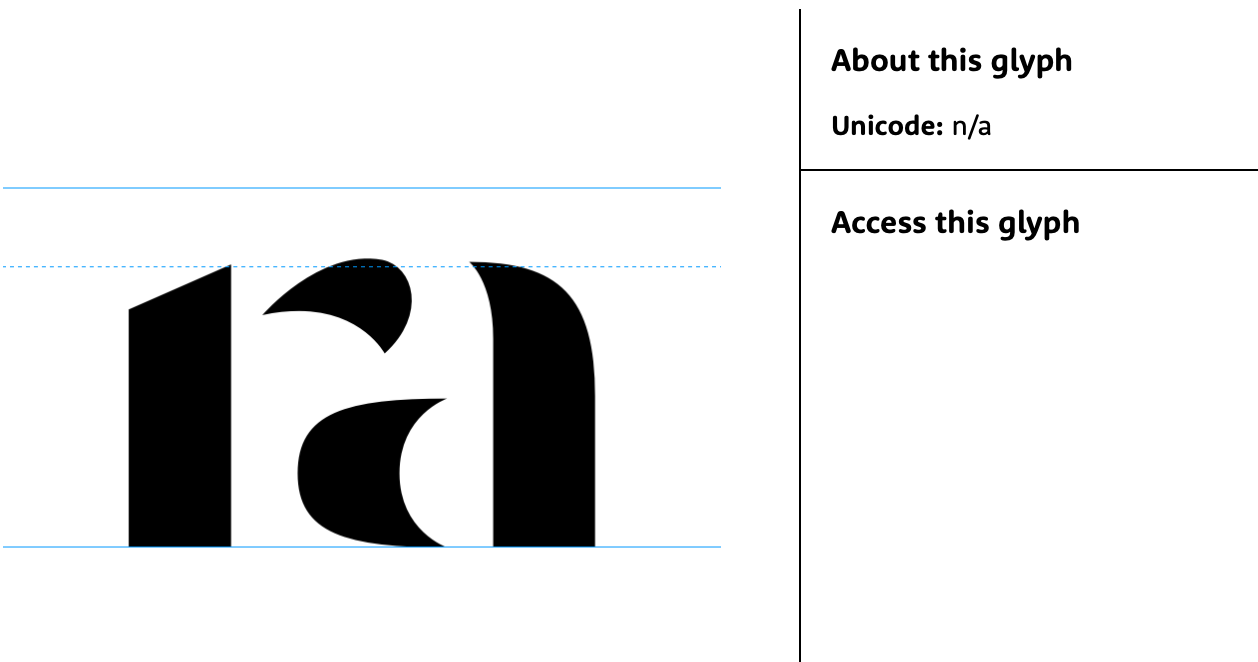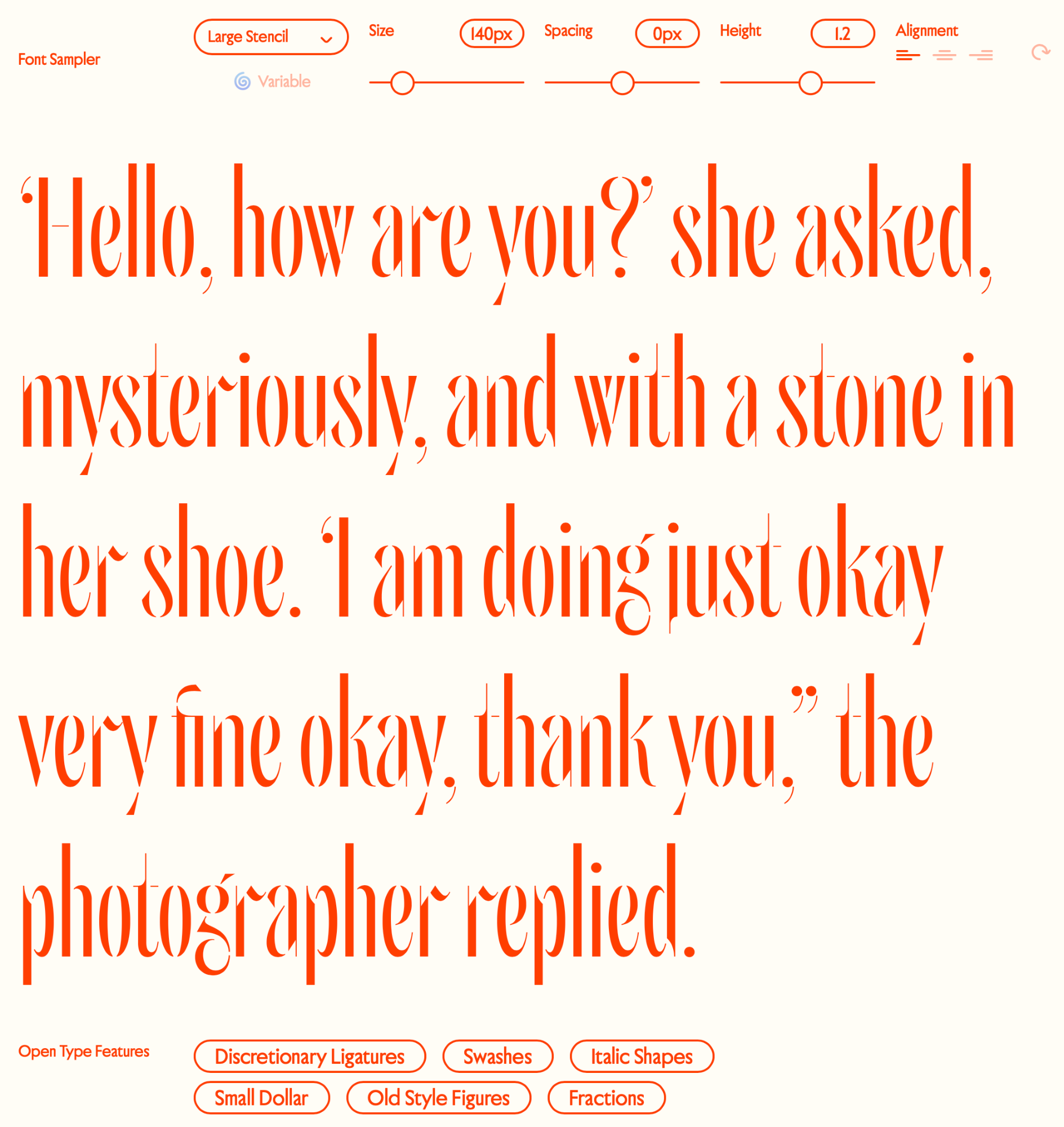
Ich überlasse das Euch Profis, aber hier schien mir eine Sammelstelle für Stencil-Schriften aller Art zu sein, auch wenn sie es nicht immer in die Liste schaffen. Und die Ligaturen scheinen mir bemerkenswert zu sein.
Wow! Habe mir die Foundry eben mal etwas genauer angesehen: Im Hinblick auf Ästhetik, Ausbau der Fonts und die Lizenzpolitik* scheinen sie ihrem Namen alle Ehre zu machen. Danke für den Hinweis!
Ästhetik
Etude von Emily Atwood, herausgegeben von Order Type Foundry
Inspired by the study of type design and experimental music techniques, the name “Etude” comes from the French verb “étudier” rooted in the meaning of “study.” True to the name, Etude is a study of the broad nib pen, the history of handwritten music notation, and the influence of Jean-Pierre Rousselet’s constructed stencil forms into three distinct weights. As the family cascades from Light to Bold, the weights become a crescendo from soft and delicate to loud and more prominent on the page.
Ich bin in den letzten Woche sicher fünf oder sechs Mal auf passende Schriften gestoßen und wollte sie hier posten. Ein kurzer Abgleich mit der Liste hat meine Pläne allerdings jedesmal durchkreuzt ... Die Liste ist einfach sehr solide!
Könnte man die Auflistung noch zwischen normalen und den hier gesuchten Stencil-Varianten aufschlüsseln?
Ich bin zum Beispiel über diese gestolpert:
TheStencil
Tripper